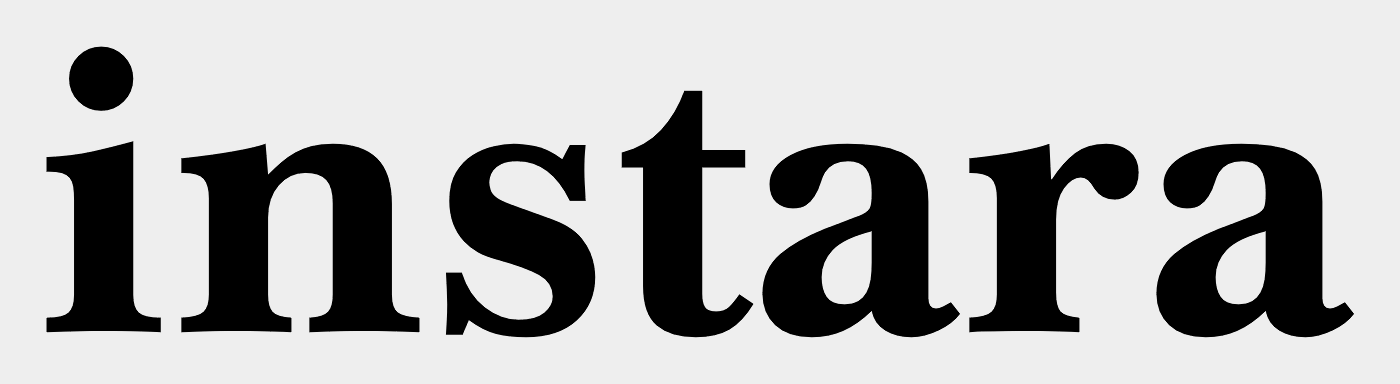
Suche Schriftart Logo
ich möchte das Logo von der Firma instara -ein privates Planungsbüro für Stadt-, Raum- und Landschaftsplanung- nachbauen. Ich bin beauftragt die Website neu zu gestalten (Habe schon die erste Fassung zu Beginn 2000 erstellt:-)
instara selbst ist sich nicht sicher, wer bzw. wie das Schriftlogo enstanden ist. Handgemacht in einem CAD Programm? Oder ist es eine gekaufte Schriftart.
Das ist eine Baskerville, auf 150 % Breite verzerrt. Welche Baskerville genau, weiß ich nicht, es gibt wirklich viele …